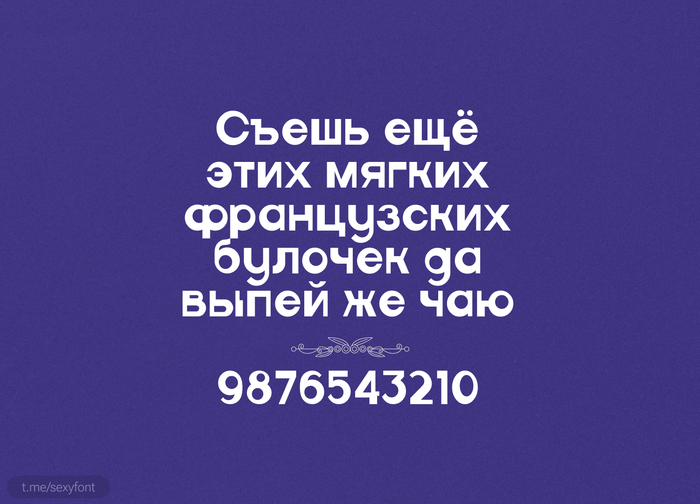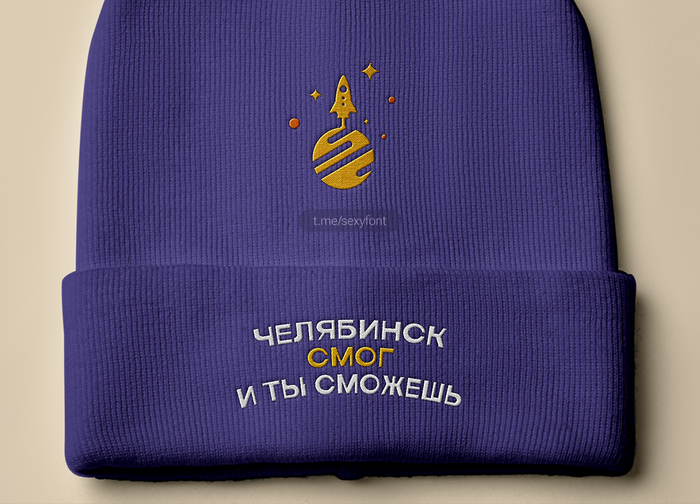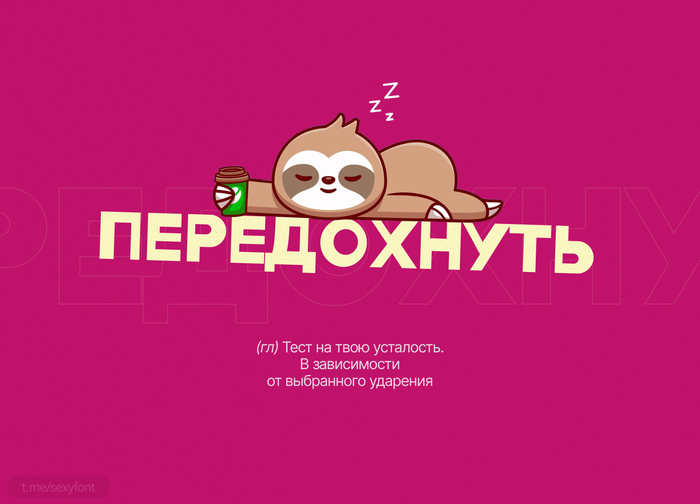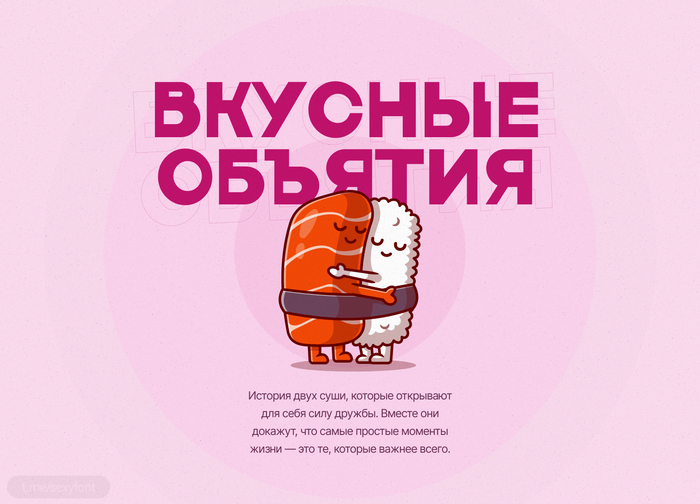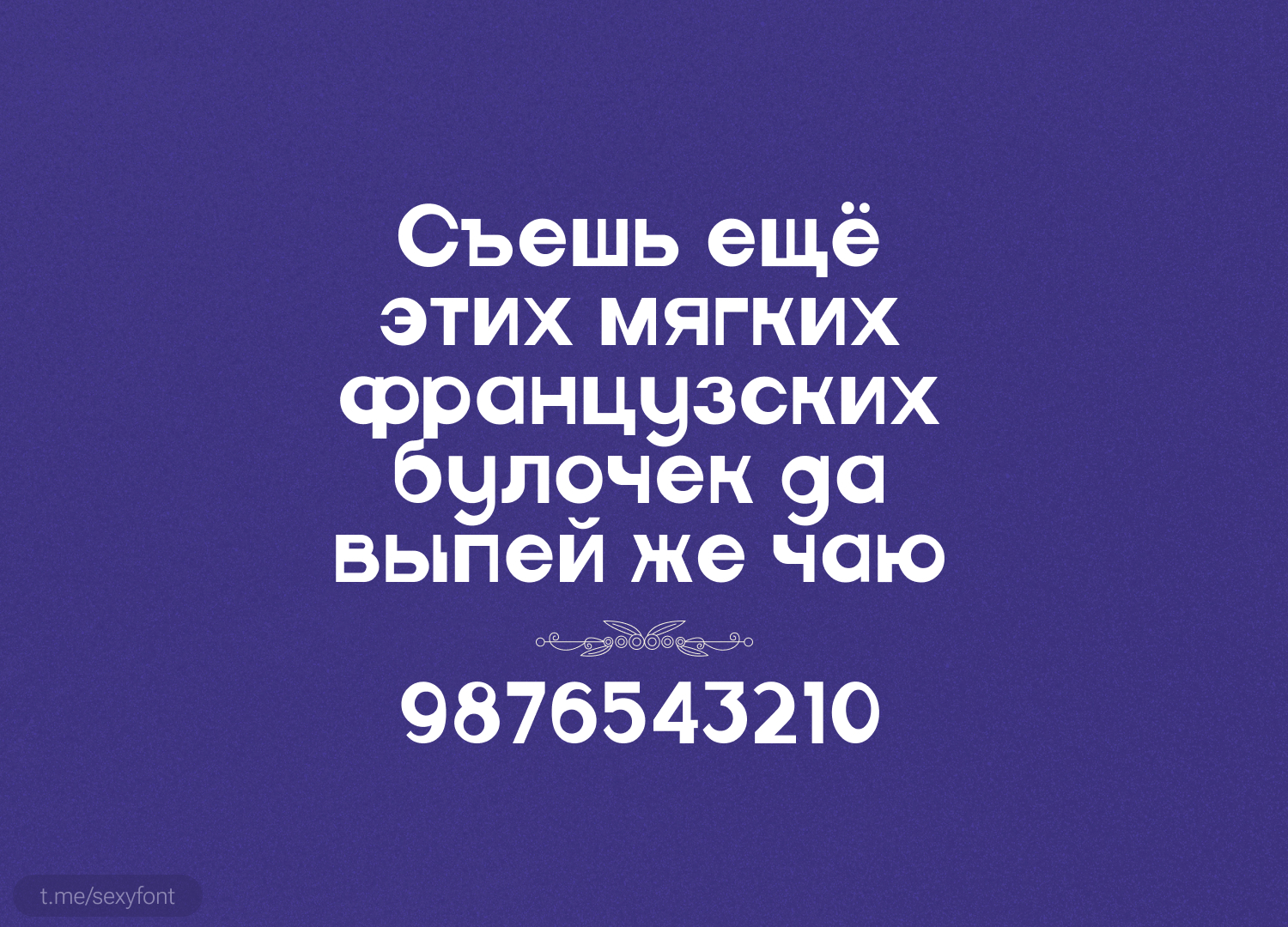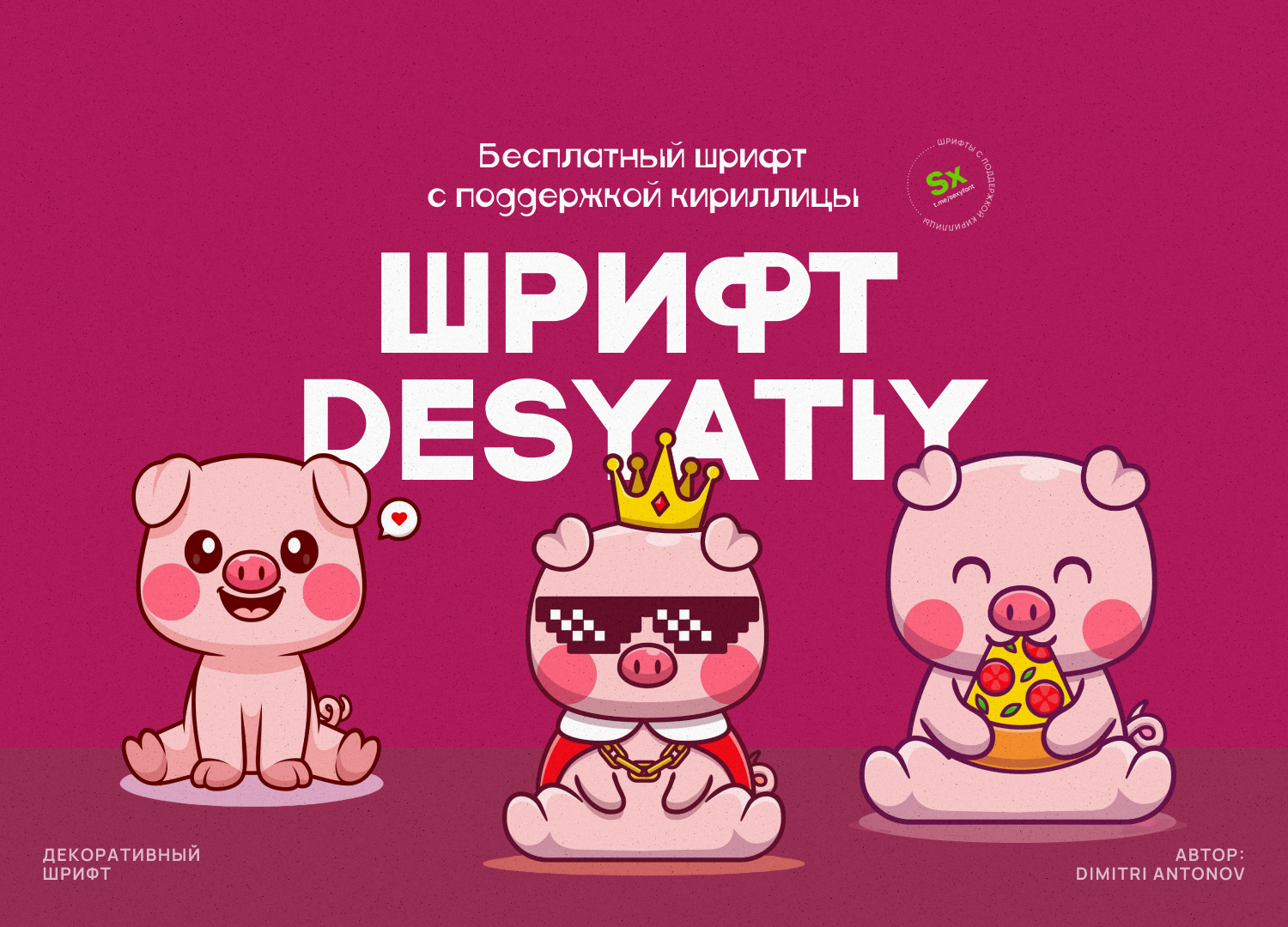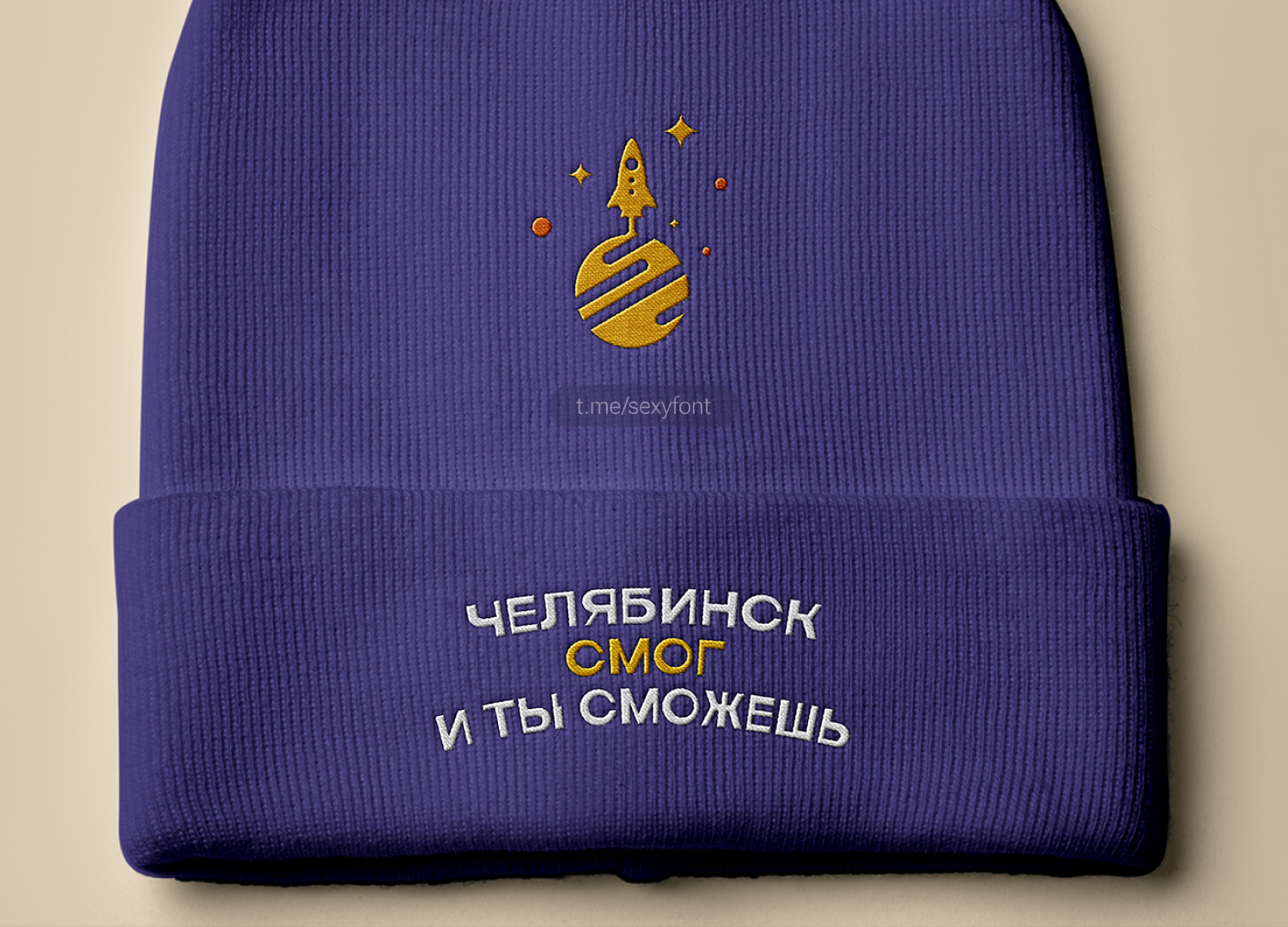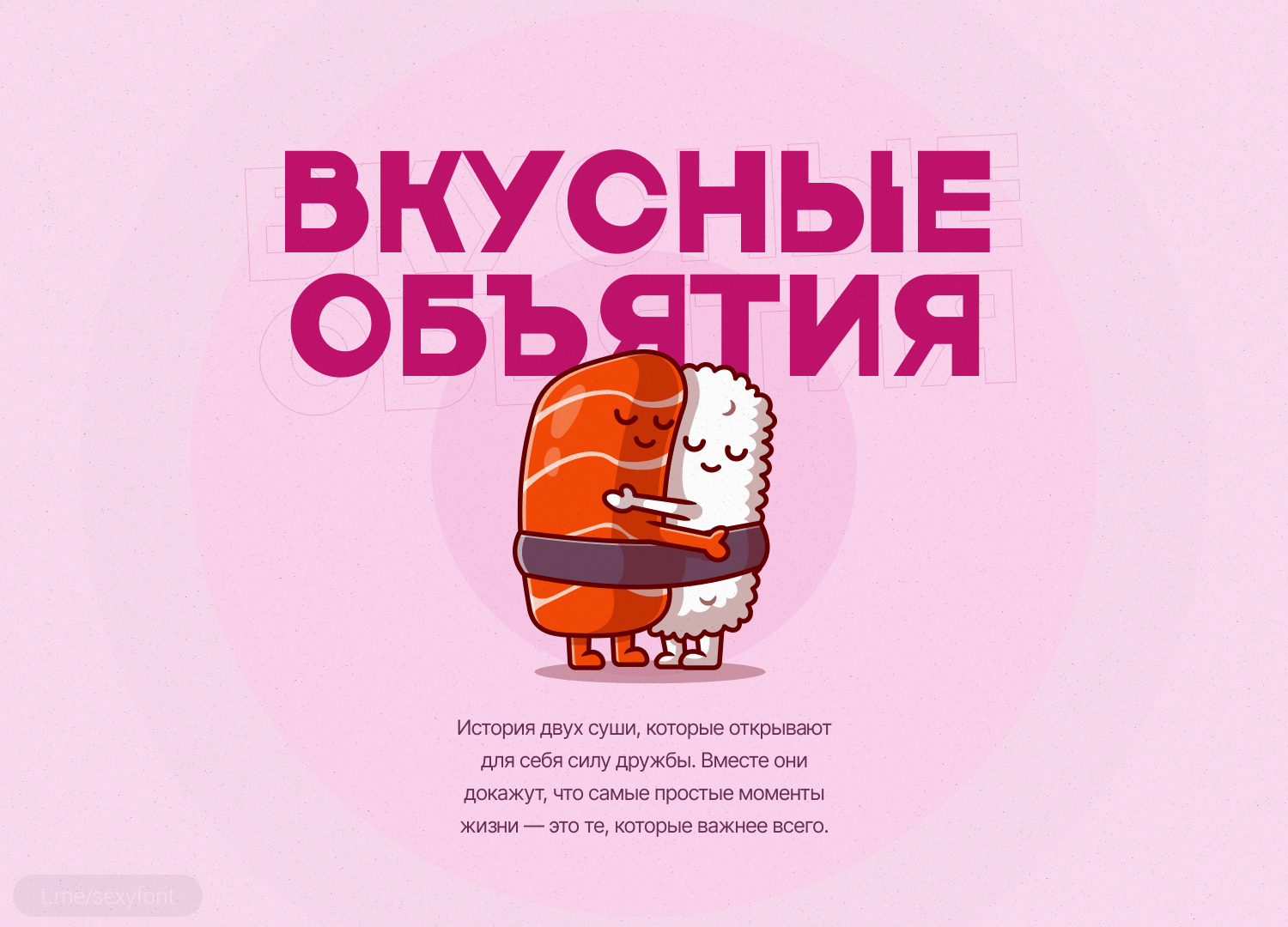
Декоративный шрифт "Десятый"
Десятый, бесплатный шрифт от Синей кривой и лично Дмитрия Антонова . Имеет 3 начертания.
Шрифт основан на необычном расположение негативного пространства глифов, результатом которого моношириный шрифт стал шрифтом с тремя разными толщинами штрихов.